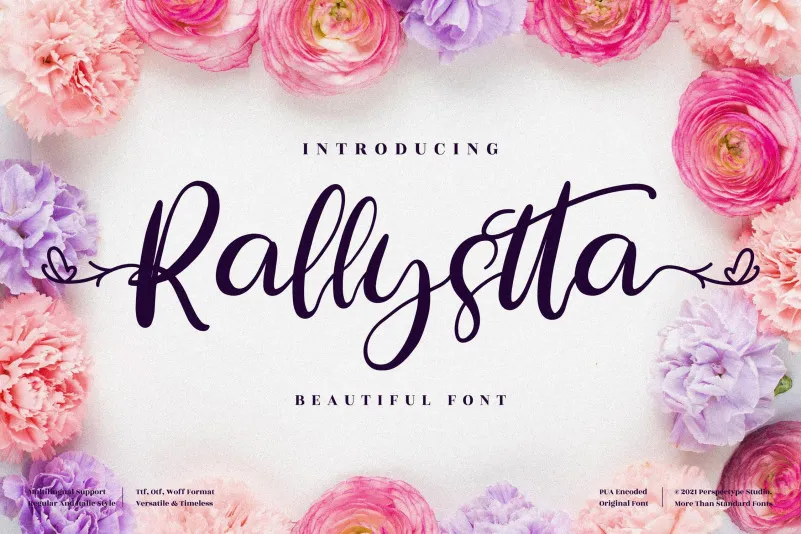
A fonte Rallystta é perfeitamente adaptada para projetos que desejam criar um ar elegante e sofisticado, seja para cartões de aniversário, convites ou até mesmo materiais corporativos mais formais. Ela flui suavemente como uma letra escrita à mão, com alternativas estilizadas e ligaturas prontas a usar que garantem um acabamento perfeito. Como fonte PUA codificada, Rallystta é muito flexível e versátil, permitindo acesso a todos os símbolos e desenhos ornamentais sem qualquer problema. Seja você designer gráfico ou editor de texto, Rallystta é o tipo script que você precisa para dar um toque elegante às suas criações, tornando cada projeto único e sofisticado.